Gentechnik-Logo … jetzt aber richtig!
Wenn wir uns im Fontblog über Logos streiten, geht es entweder um das inhaltliche Konzept oder die Gestaltungsqualität. Das war gestern anders, beim neuen Kennzeichen für Lebensmittel ohne Gentechnik, vorgestellt vom Bundesministerium für Ernährung, Landwirtschaft und Verbraucherschutz: Die Ausführung der downloadbaren Datei geriet in die Kritik. Was das Ministerium als druckfähige Version bezeichnet, ist eine miserabel ausgeführte Reinzeichnung, noch dazu als minderwertige Pixelgrafik abgelegt. Schon bald gab es Verbesserungsvorschläge in den Kommentaren … plus formale Kritik, aber da wollen wir uns mal nicht einmischen.
Seit heute Abend liegt uns eine professionell digitalisierte Version des Logos vor (oben), wie sie eigentlich das Ministerium hätte anbieten sollen. Sie stammt aus dem Hause du Carrois, das sind Ralph und Jenny du Carrois, zwei Spitzendesigner, deren Biografie hier nachzulesen ist. Wer Ralph noch nicht über seine Schrift Maurea kannte, wird spätestens durch Erik Spiekermanns letzte Schrift Axel auf seinen Namen gestoßen sein. Doch Ralph du Carrois digitalisierte nicht nur Axel, sondern auch die Corporate Fonts von Gravis, Kia und die neuen Piktogramme der überarbeiteten heute-Nachrichten fürs ZDF.
Nachfolgend beschreibt Ralph seine rund 2-stündige Fontlab-Arbeit am Gentechnik-Logo in allen Details, worum ich ihn ausdrücklich bat. Fontblog wird nicht nur von Designexperten gelesen, denen die Fehler einer schlechten Digitalisierung sofort ins Auge springen, sondern auch von Laien, die möglicherweise Design beauftragen, einkaufen oder vertreiben … wie zum Beispiel Bundesministerien. Ihnen widmen wir diesen Beitrag, nicht ohne zunächst das Original-Logo (links) und die Überarbeitung (rechts) gegenüber zu stellen (Vergrößerung auf Mausklick):
The Making of Ohne-Gentechnik-Logo-Reinzeichnung, von Ralph du Carrois
Ich habe mir gestern das PDF geladen und war erschüttert über die Qualität der Vektoren. Das ist Datenmüll, bestenfalls eine Skizze, auf der man aufbauen kann. Der Rhombus und seine Konturen sind nicht vertretbar: Stützpunkte an den Extrema fehlen schlicht, Tangenten kommen hakig aus den Geraden, das ganze Ding ist nicht symmetrisch, in keiner Achse.
Für einen erfahrenen Grafiker oder Typedesigner ist es ein leichtes den, nennen wir ihn Entwurf, zu einen offiziellen Zeichen zu machen. Dabei geht es gar nicht um inhaltliche Themen, wie adidas-Ähnlichkeit, legalize it, Hanf, MixedCase-T oder Corporate S mal leicht gesperrt, mal eng gesetzt. Es geht schlicht um die handwerkliche Qualität des Produkts.
Geht man einen Schritt weiter, fällt bei der verwendeten Schrift auf, dass sie nicht glücklich gewählt wurde. Die Corporate S verschließt sich sehr und ist für Kleinstanwendungen einfach nicht gemacht. Doch auch hier muss man nicht gleich mit dem Prügel draufhauen und eine super optimierte Type für sehr kleine Low-quality-prints auswählen. Man kann, mit etwas Feingefühl, viel verbessern:
- h wird so breit wie n
- die Schwüngchen am n-Stamm werden entfernt, da sie in den meisten Anwendungen mehr stören als helfen werden
- e wird unten leicht geöffnet. Die Intarsie wird minimal an den Bogenausgängen der Basis nur über die BCPs vergrößert
- G wird oben ebenfalls leicht geöffnet und der sehr tiefe Querstrich etwas angehoben
- T ist zu schmal und wenn es breiter wird, zu weit vom e entfernt. So wie es nun nun gelöst ist, passt es besser und bleibt trotzdem ein Störer. Zumindest in unseren lateinischen Augen. Kyrillische Augen sind dieses Zeichen gewöhnt, wenn auch nicht in Verbindung mit dem kleinen lateinischen n ;)
- Weiter geht es mit den c, das in der Corporate S sehr verschlossen ist und nun auch wenig zum weiter geöffneten e und G passen mag. Der rechte Teil wird verbreitert, die Enden geöffnet und angeschrägt
- Jetzt kann das h etwas näher an das c. So gewinnen wir Platz zurück, den wir vorher für das T verschwendet haben
- Der i-Punkt wird etwas größer
- Zuletzt der Zusammenschluss am k: das ist nicht notwendig, passt aber in meinen Augen viel besser zur Gesamtanmutung und spart Platz, der für T und c benötigt wurde
Das Laub-Symbol war zu detailreich. Das Blattwerk ist nun formal einfacher und durch den größeren Abstand der Blätter und das weniger spitze Mittelblatt weiter weg von adidas und Hanf, und zusätzlich besser in kleinen Anwendungen. Ausserdem piekst es nicht so von unten in den Text. Der Stamm ist dicker. Der war bei der Ausgangsversion zu dünn für die wichtigsten Anwendungen. Das Blatt wurde auch etwas größer.
Der Rhombus ist nun achsensymmetrisch und seine Ecken sauber, mit allen nötigen Punkten und optisch an die Strichstärke des Rahmens angepasst. Die seitlichen Ecken sind numerisch etwas dicker als die obere und untere Ecke. Optisch sehen sie so harmonischer aus.
Fertig.
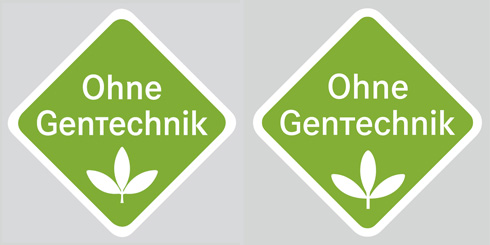
Den Satz werden die Laien lieben :) Aber eigentlich hätte man für ein Zeichen das so klein abgedruckt werden soll, einfach eine offenere Type nehmen sollen.
Für mich wirkt das Logo recht frisch und unbelastet. Dennoch stolpert man über das Versal-T automatisch. Wieso wurde das T grossgeschrieben? Welcher Gedanke steckt dahinter?